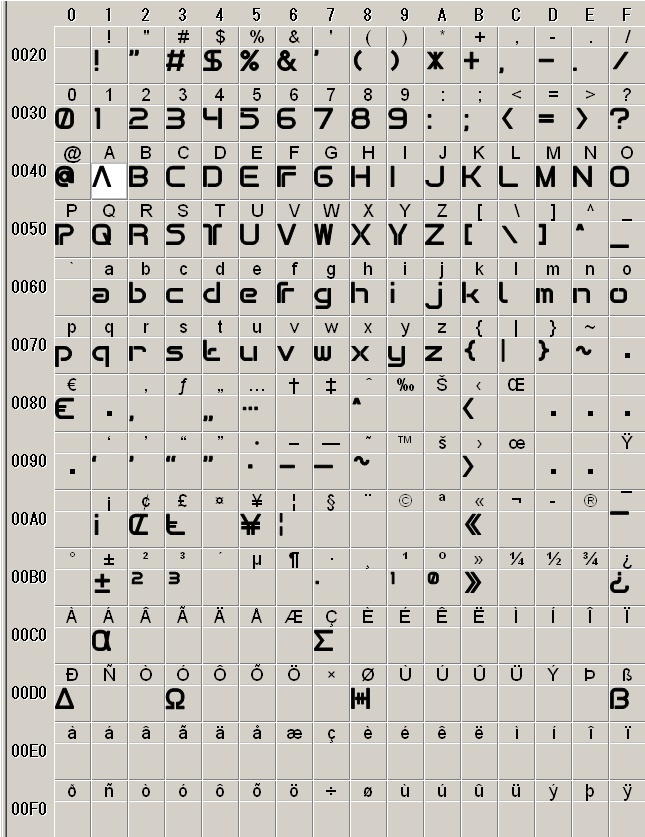
UGSF2800風フォント Type.Oto&Mit Opt.1 Ver1.00
「しんぐんデストロ~イ!」「NewSpaceOrder」などに登場する 「UGSF2800」と呼ばれるフォントを判読性を高めるため独自の改良、最適化を 施したフォントファミリーです。 【利用規約】 ○個人利用の範囲でご自由にお使いください。 ○公式の権利を侵害する目的はありません。著作権は各権利者に帰属します。 ○再配布/商用利用/公式に迷惑をかけるような行為全般を禁止します。 ○当フォントを使用して発生したいかなる障害及び事故等についても、制作者及び著作権所有者は一切その責任を負いません。 ○当フォントは予告なく改良、配布終了することがあります。 【更新履歴】 2016/07/20:配布開始(ver.1.00) 改良や追加があれば更新します。